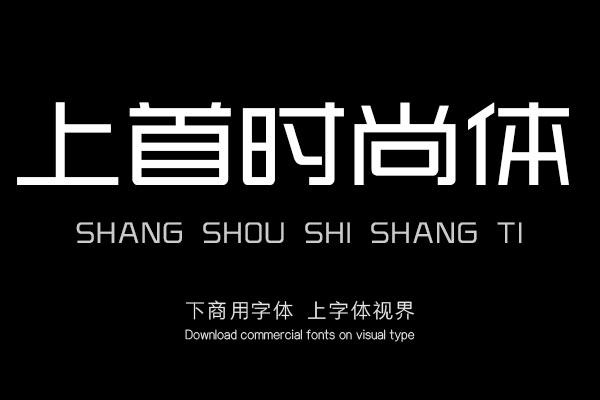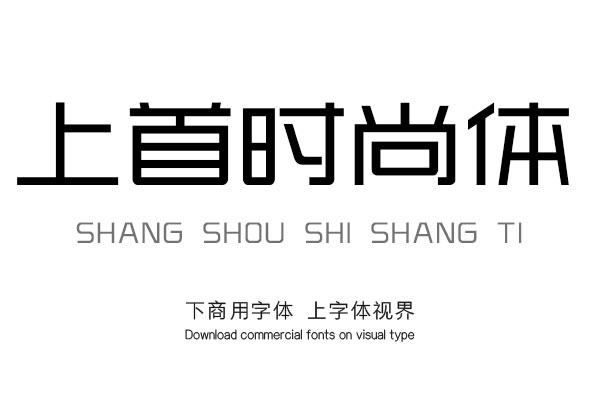
上首时尚体,字体整体风格时尚简洁又不失大气,字体笔画竖折处做圆角处理,是此套字库的亮点。整体特征坚硬、有力;具有现代、国际化的指向性,适用于高端的商业广告、商业......购买须知:“下载服务费”与“字体VIP”所获得字体 仅用于个人非商用, 商用请联系付费授权。本字体为电脑用字,手机没有root权限不支持直接手机换字(手机如何root,请自行百度搜索教程)。购买前请先 了解清楚后再付款 ,字体为虚拟产品无法回收 一旦购买不支持退款。